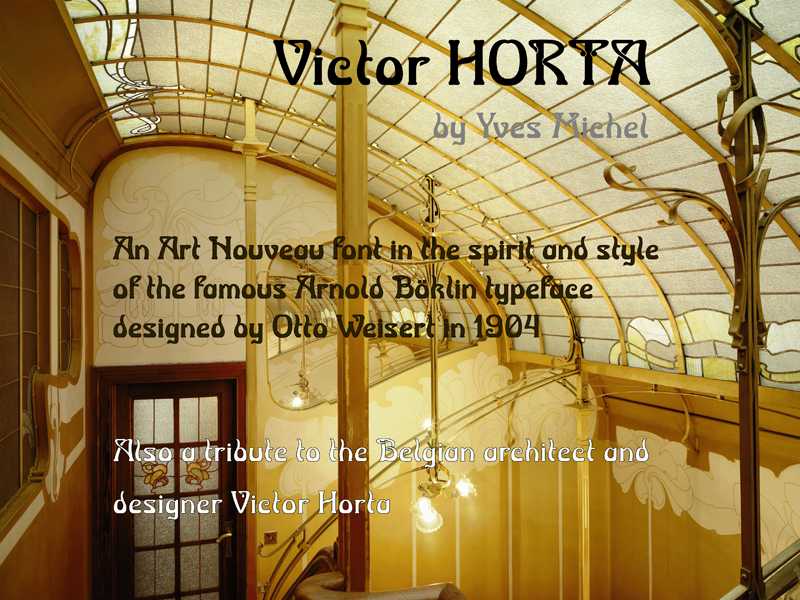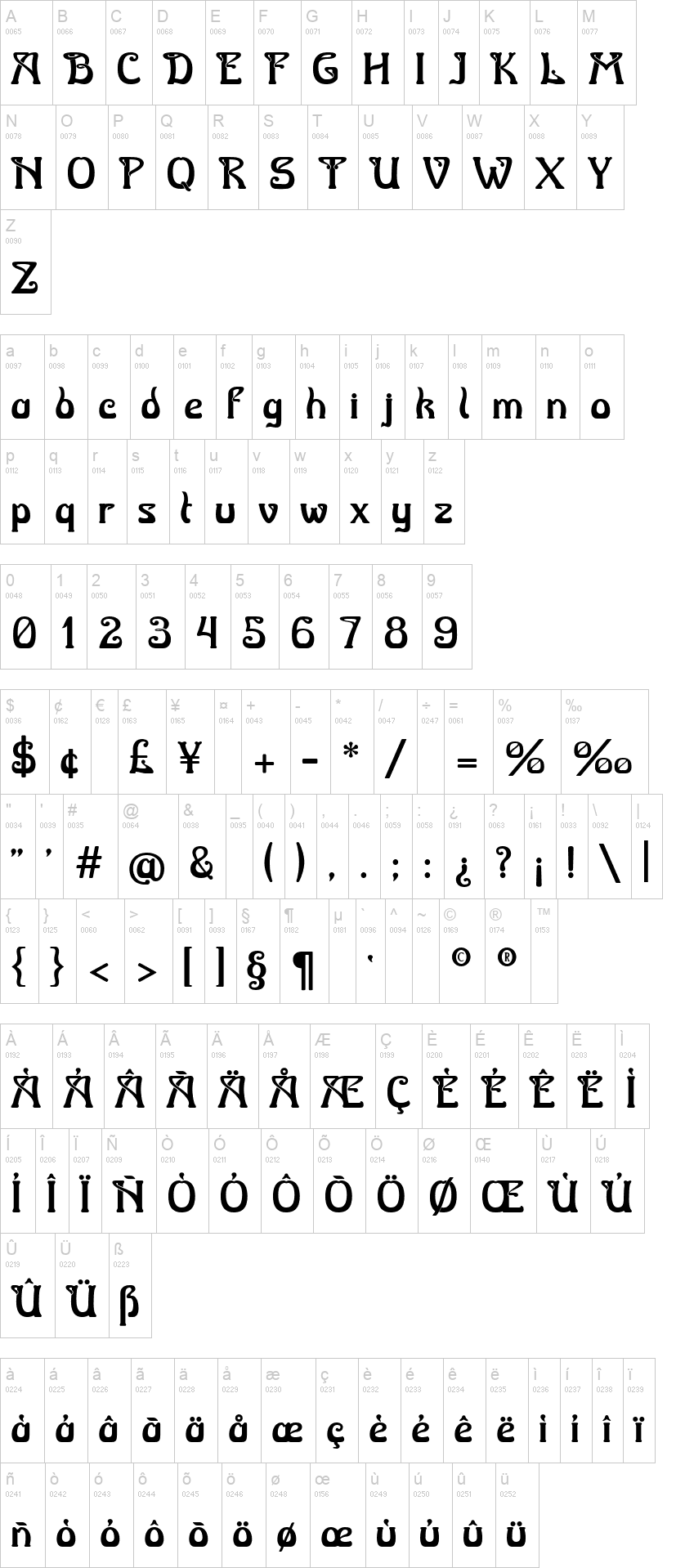
Note of the authorPolice en hommage à Victor Horta, célèbre architecte et designer belge, un des fondateurs de l'Art Nouveau. Dans l'esprit et le style de la police Arnold Böcklin dessinée par Otto Weisert en 1904.
A typeface in tribute to Victor Horta, famous Belgian architect and designer, one of the founders of the Art Nouveau movement. In the spirit and style of the Arnold Böcklin typeface designed by Otto Weisert in 1904.